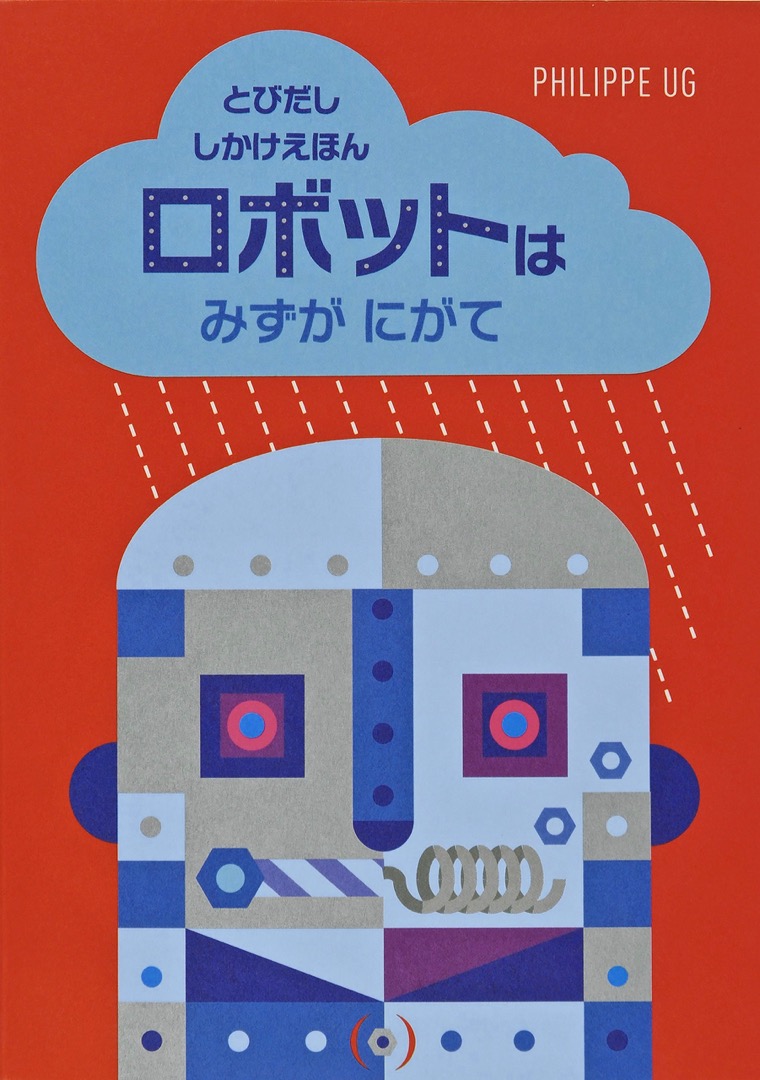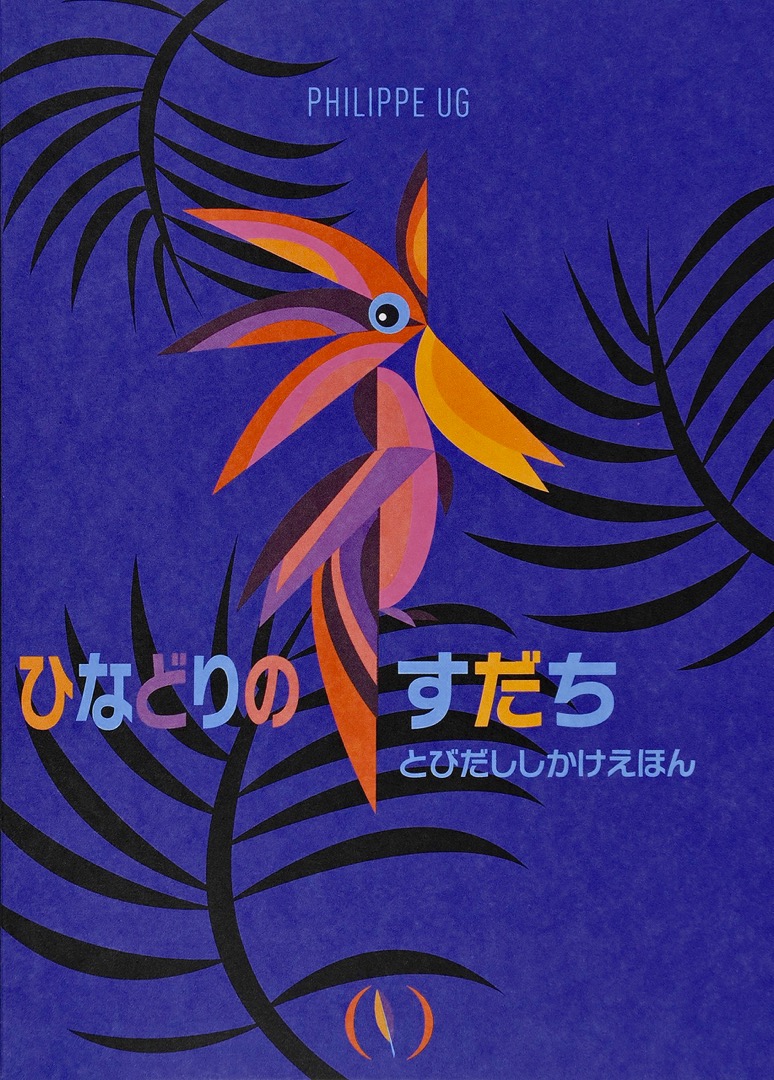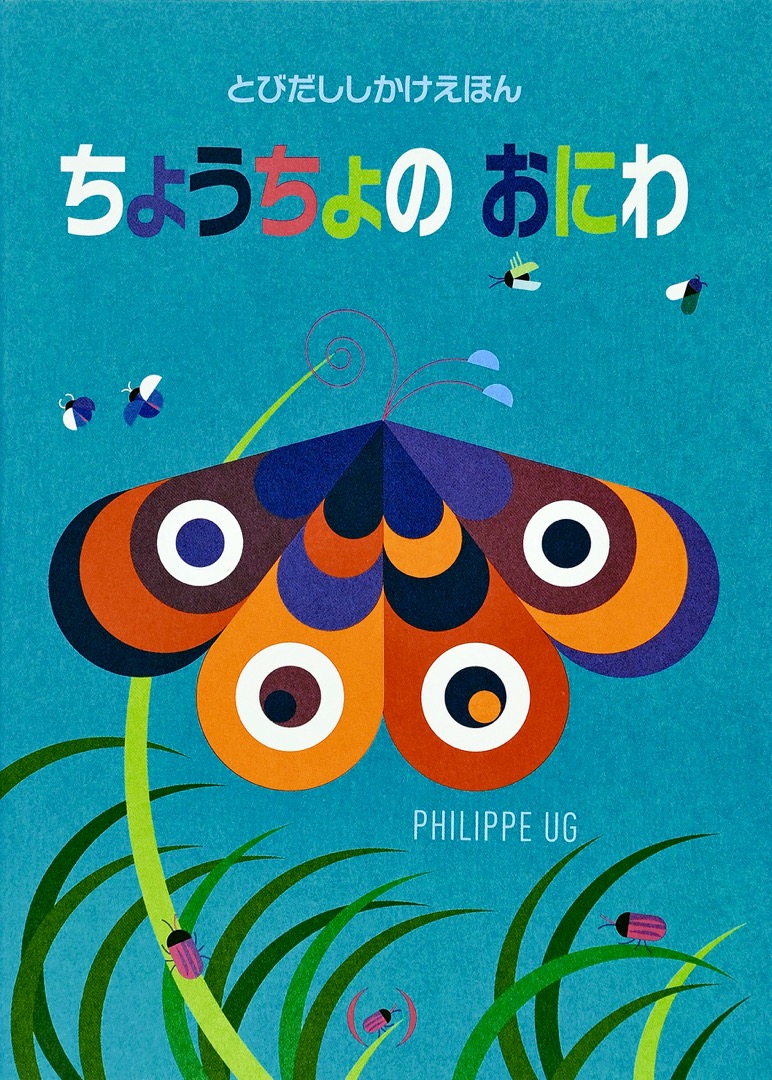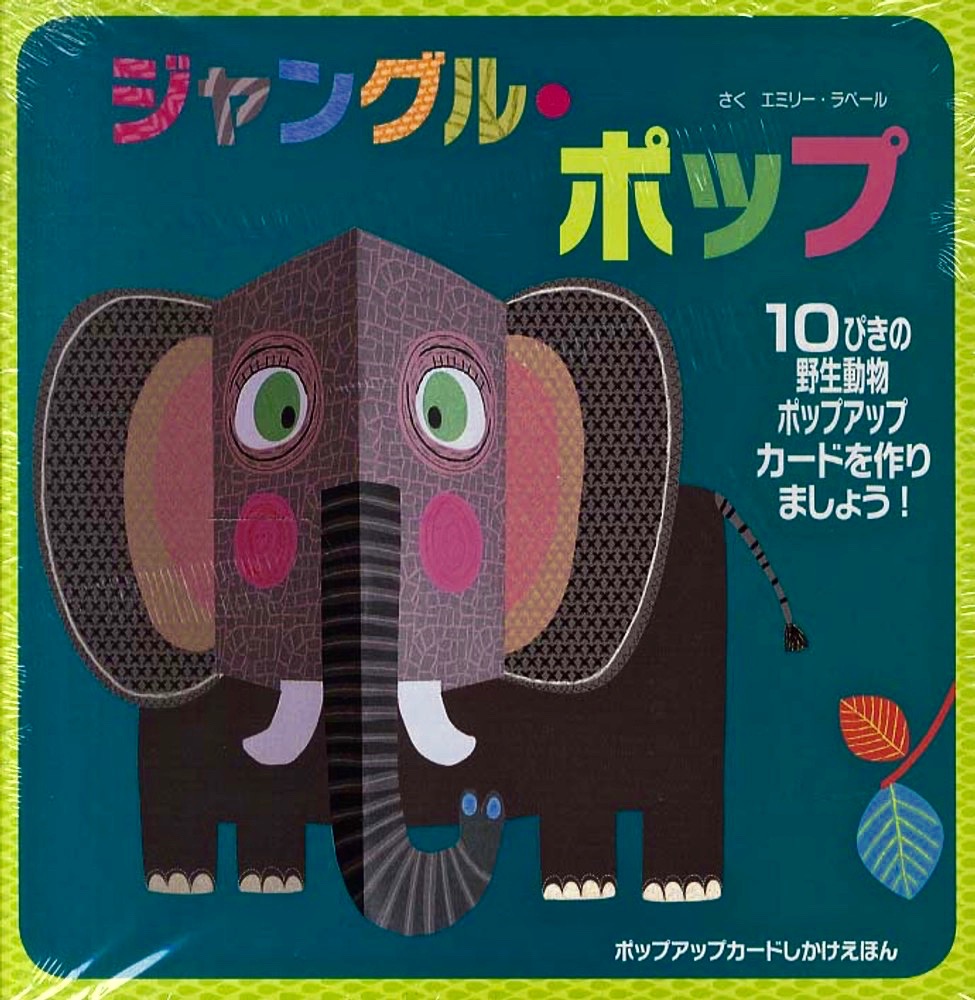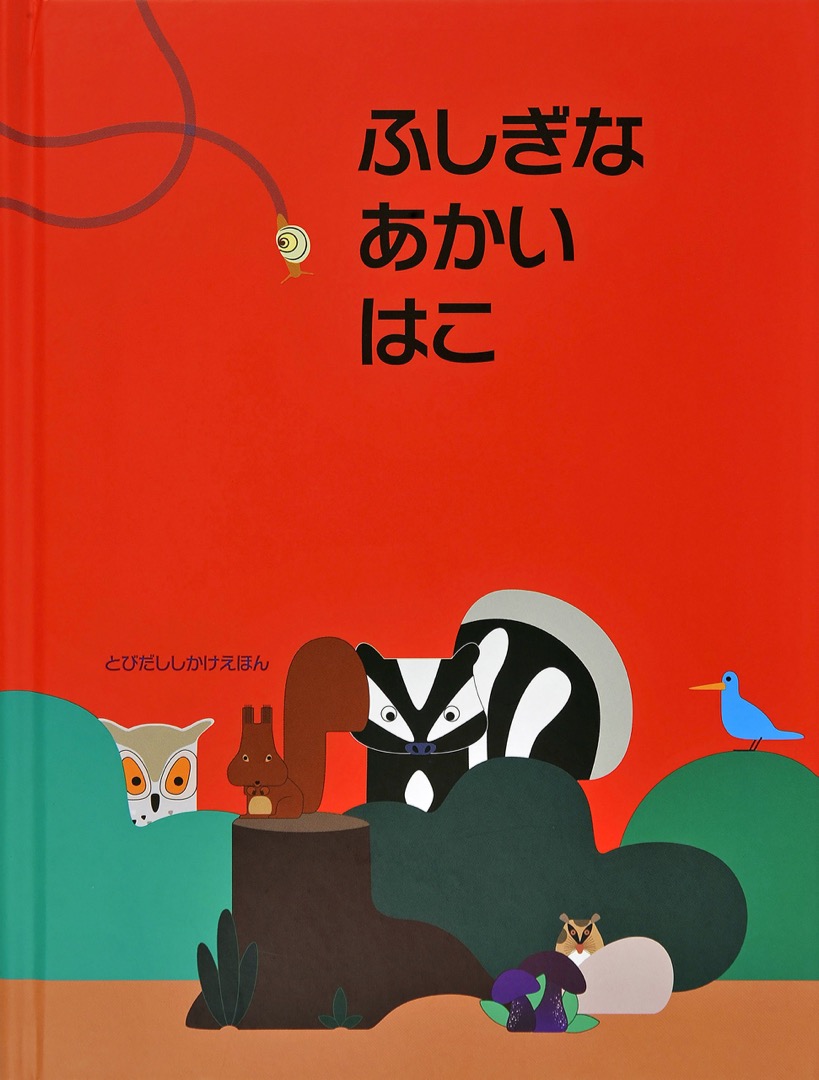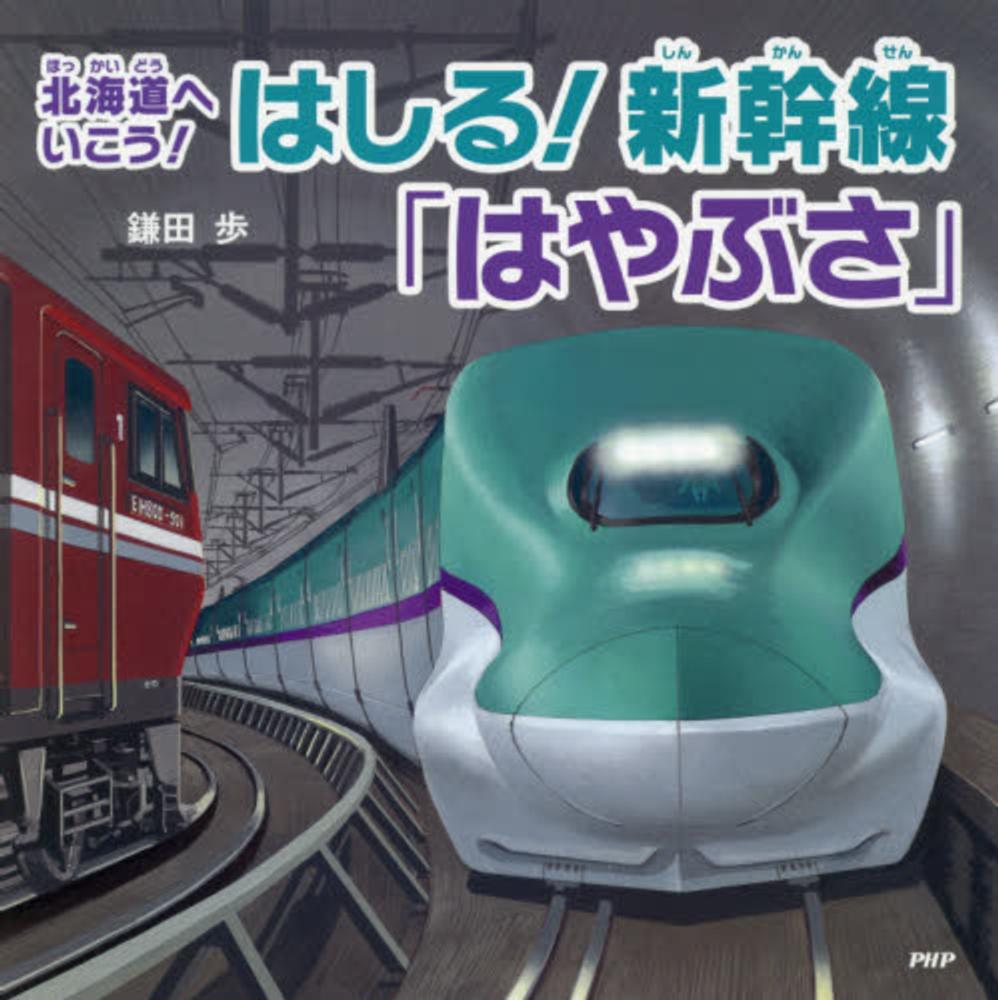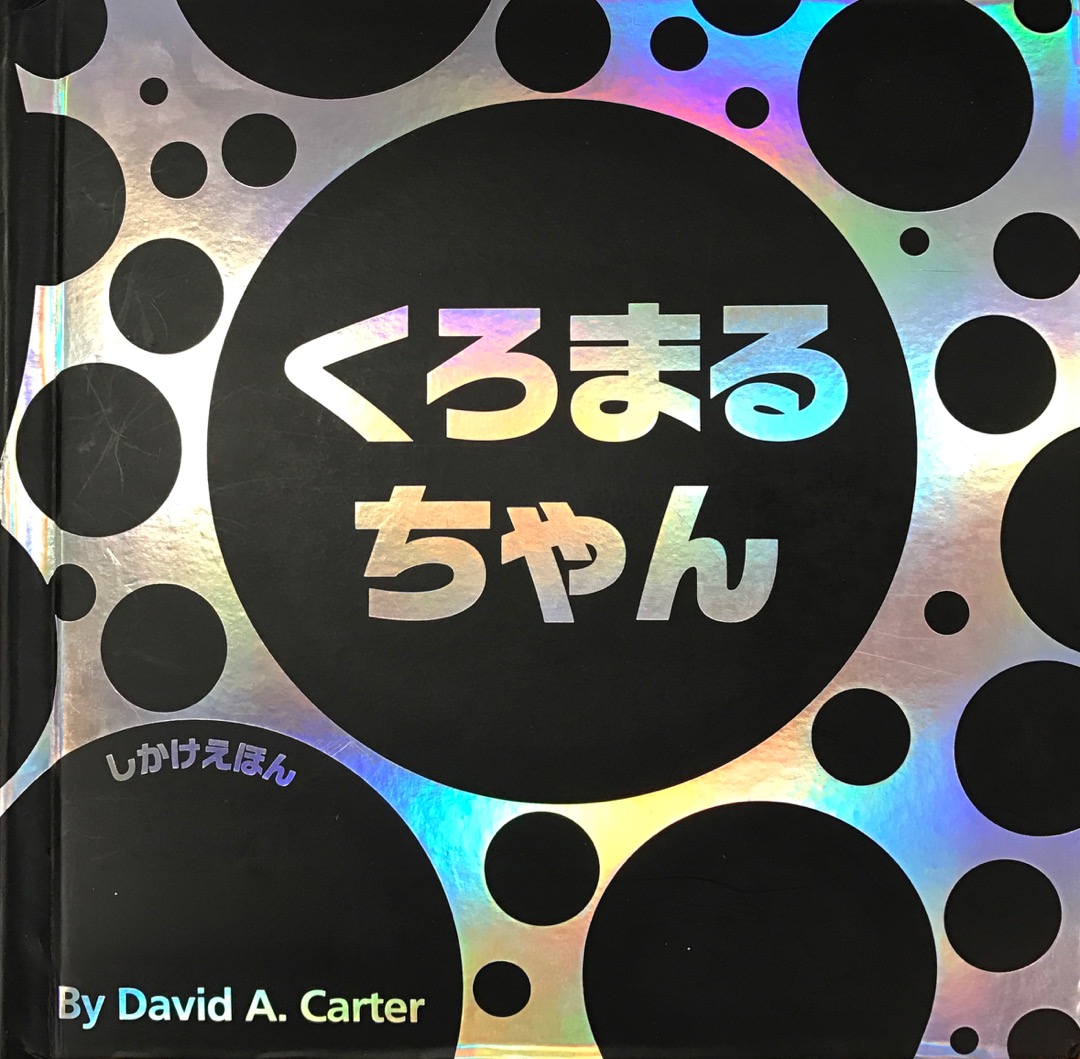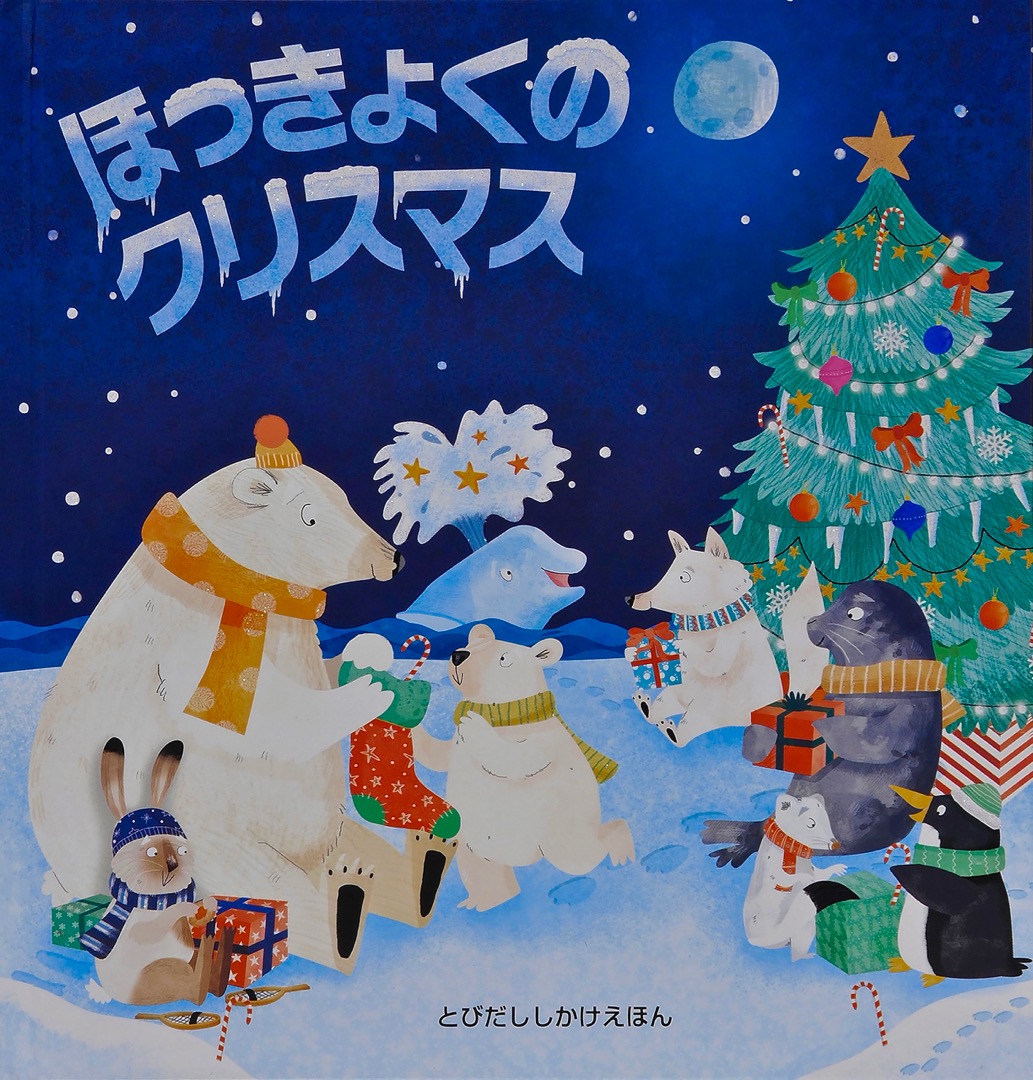
これなあに? さとうゆたか
書名:アンパンマン おしゃべりどうぶつずかん
著者:やなせたかし/フレーベル館・TMS・NTV
発行:セガトイズ
たべるってたのしい! さとうゆたか
書名:まいにちつかう はしってすごい!
著者:谷田貝公昭、柴山 ヒデアキ
発行:少年写真新聞社
本の表紙 さとうゆたか
書名:パッチワークパターン集1050
著者:中嶋由美子
発行:ブティック社
テレビ番組 さとうゆたか
この書体、テレビでは多用されているので、見飽きてるかもしれませんが…。
足立区出身のANZEN漫才。
9年ほど前から自分も足立区に住んでいるので、応援している。
アメトーーク! さとうゆたか
テレビ朝日のアメトーーク!
愛の戦士たち さとうゆたか
ヤマトと最下段の2行。
書名:小説宇宙戦艦ヤマト2202
原作:西崎義展
ストーリー:福井晴敏
小説:皆川ゆか
発行:KADOKAWA
地元の役所のポスター takumi
地元の役所の中に貼られていたポスターで、ニタラゴルイカフォントが使われていました。
吹き出しの中の文字ですね。
「話」の言偏の1画目でわかりました(笑)。
吹き出しの中の、小さい文字部分ですね…。
知育ずかん さとうゆたか
書名:はじめてのきょうりゅうずかん
著者:講談社ビーシー
発行:講談社
宿泊施設ロゴ さとうゆたか
北千住駅の近くにあった。
施設の案内。
図鑑 さとうゆたか
書名:はじめての のりものずかん
著者:講談社ビーシー
発行:講談社
同じシリーズ さとうゆたか
書名:はじめての どうぶつずかん
著者:講談社ビーシー
発行:講談社
番宣ビデオのタイトル さとうゆたか
ムロツヨシの顔面ドラマ「俺たちナイスバディー」